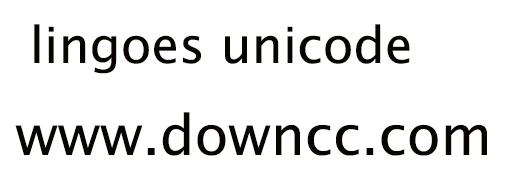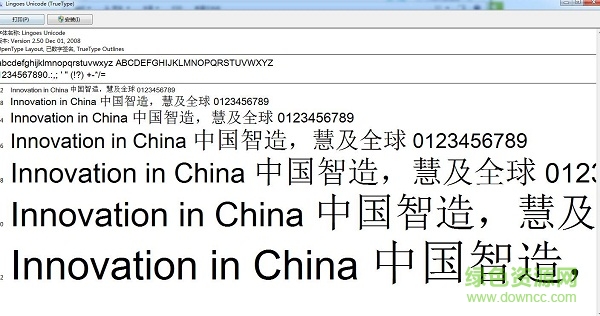
lingoes unicode字體是靈格斯詞霸軟件中的一款音標(biāo)字體,支持國(guó)際音標(biāo)的輸入顯示,字形清晰,實(shí)用性廣泛,本站還有更多特色符號(hào)字體可供下載,歡迎需要的朋友免費(fèi)體驗(yàn)!
Lingoes Unicode 是由靈格斯推出的一款音標(biāo)字體,支持國(guó)際音標(biāo)、漢語(yǔ)拼音、以及大部分 Latin 語(yǔ)系的音標(biāo)顯示和打印,安裝后即可正常顯示注意英語(yǔ)音標(biāo)。